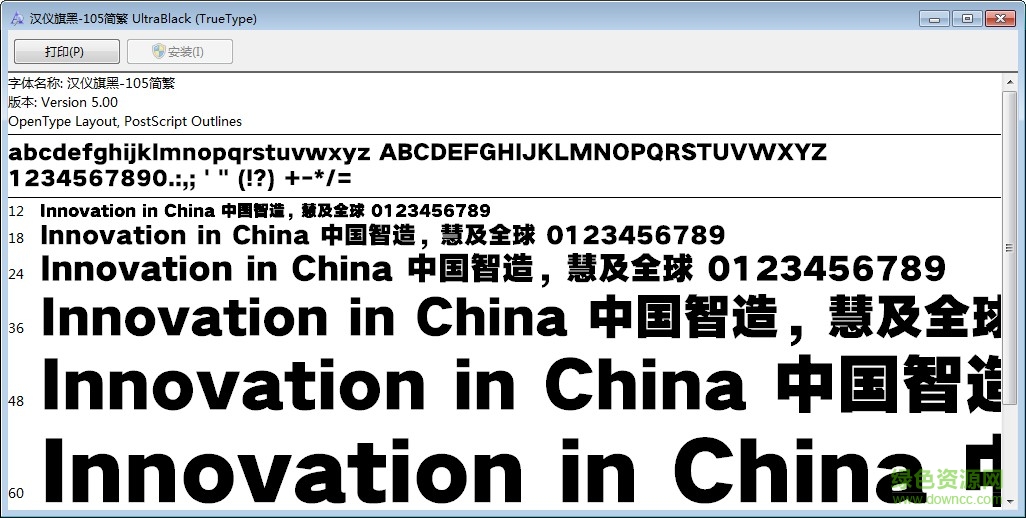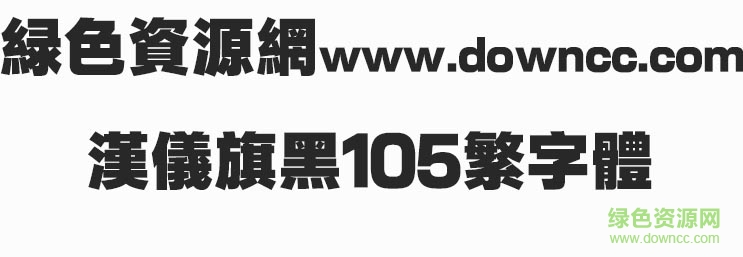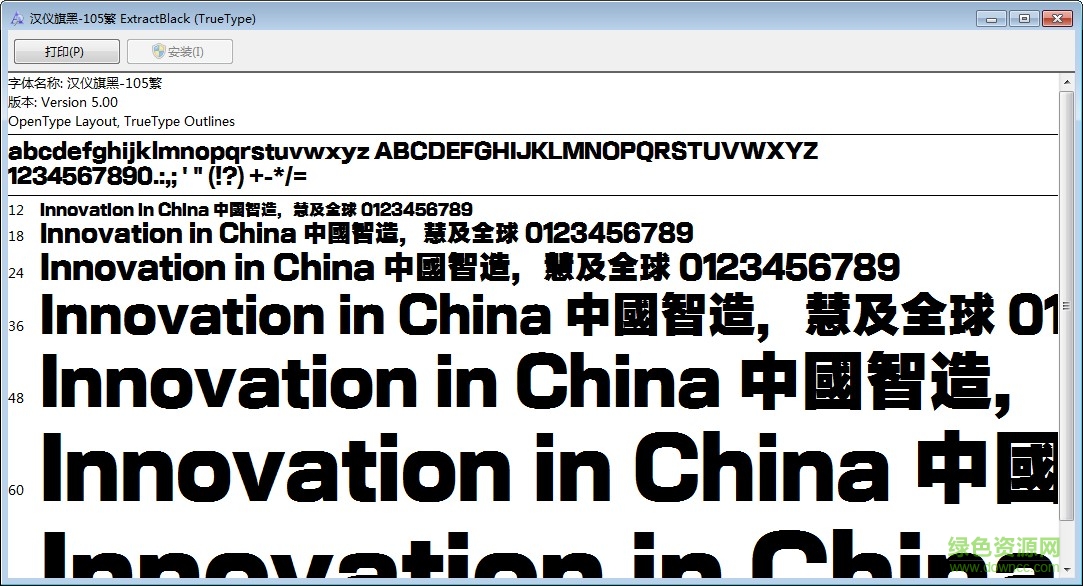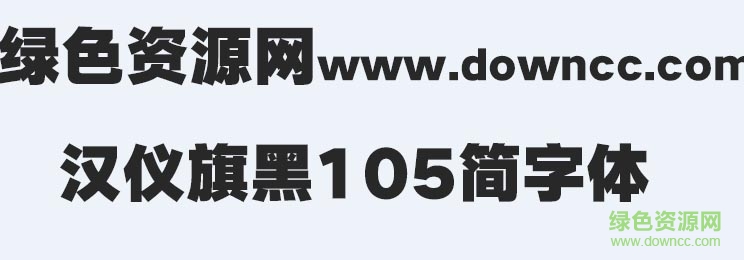
漢儀旗黑105簡繁字體是小編需要此款字體的朋友帶來的簡體+繁體字體,這種字體最大的特點(diǎn)就是特別粗、特別黑,是很有氣勢的一款字體,小編為大家提供這款字體的下載地址,歡迎有需要的朋友來綠色資源網(wǎng)下載。
漢儀旗黑105字體其實(shí)是一款非常粗的黑體字體,字體端正大方,筆畫粗黑,整體效果非常出色,很適合用于書法題字、題詞等,還可以用于宣傳、廣告、商標(biāo)、標(biāo)語、黑板報(bào)等領(lǐng)域。用途非常廣泛。